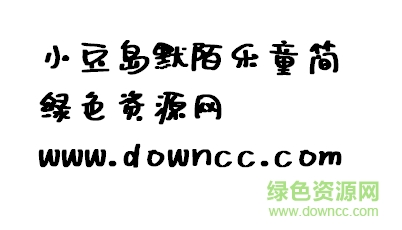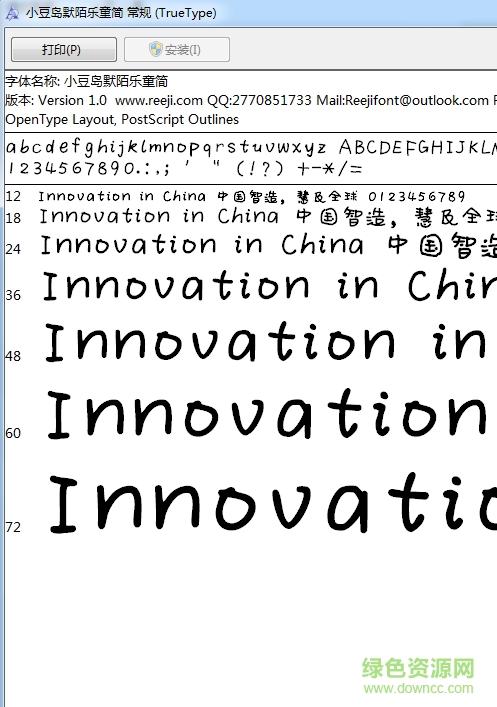
小豆島默陌樂童字體是一款小清新可愛的時(shí)尚手寫字體,字體筆畫透露著天真童趣的氣息,整體給人十分優(yōu)雅脫俗的感覺,喜歡的小伙伴們快來下載體驗(yàn)吧!
小豆島默陌樂童簡字體家族系列主要提供常規(guī)等字體風(fēng)格樣式,廣泛應(yīng)用于企業(yè)名稱、會(huì)場布置、、商標(biāo)、標(biāo)語、展覽會(huì)、宣傳、廣告、黑板報(bào),以及商品包裝和裝潢,各類廣告、報(bào)刊雜志和書籍的裝帖上等,越來越被大眾喜歡。